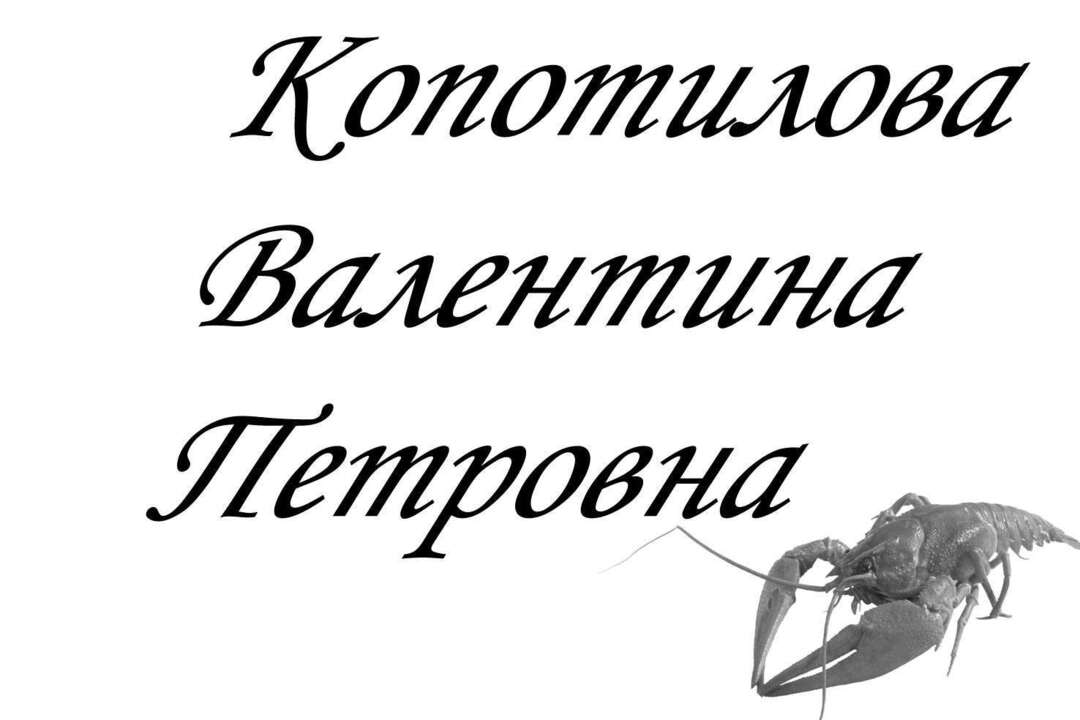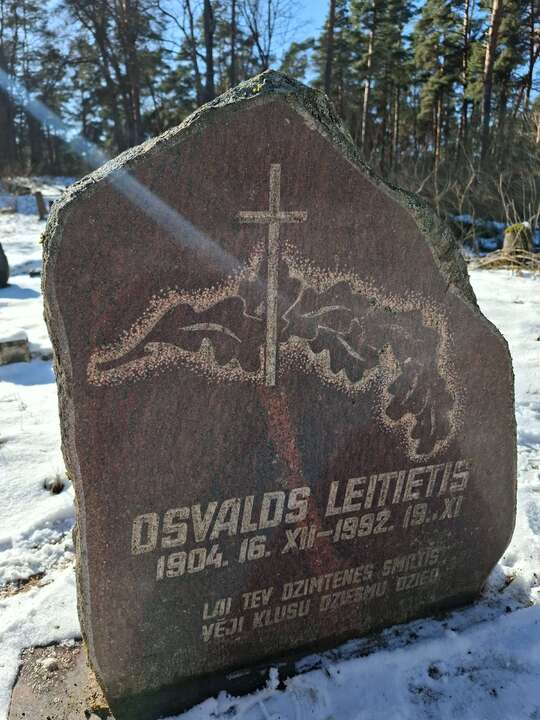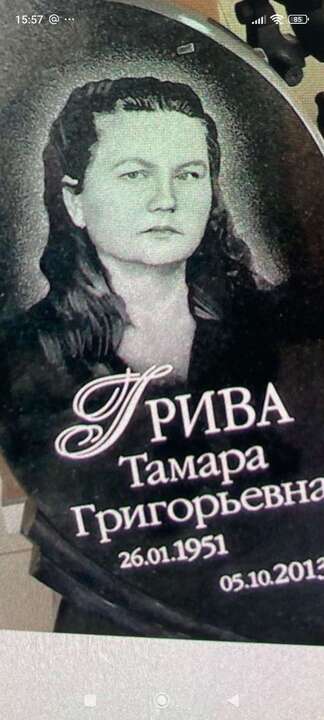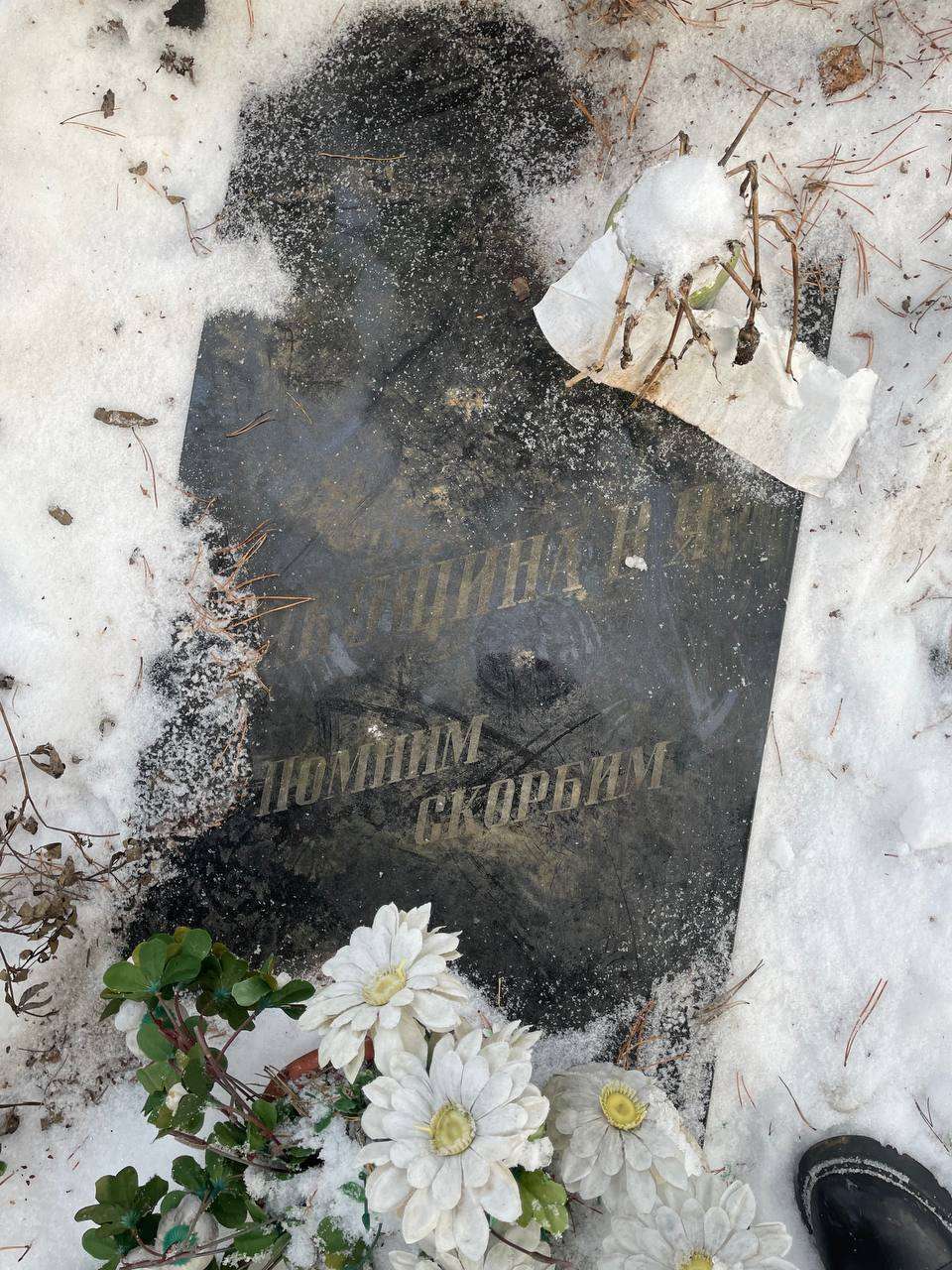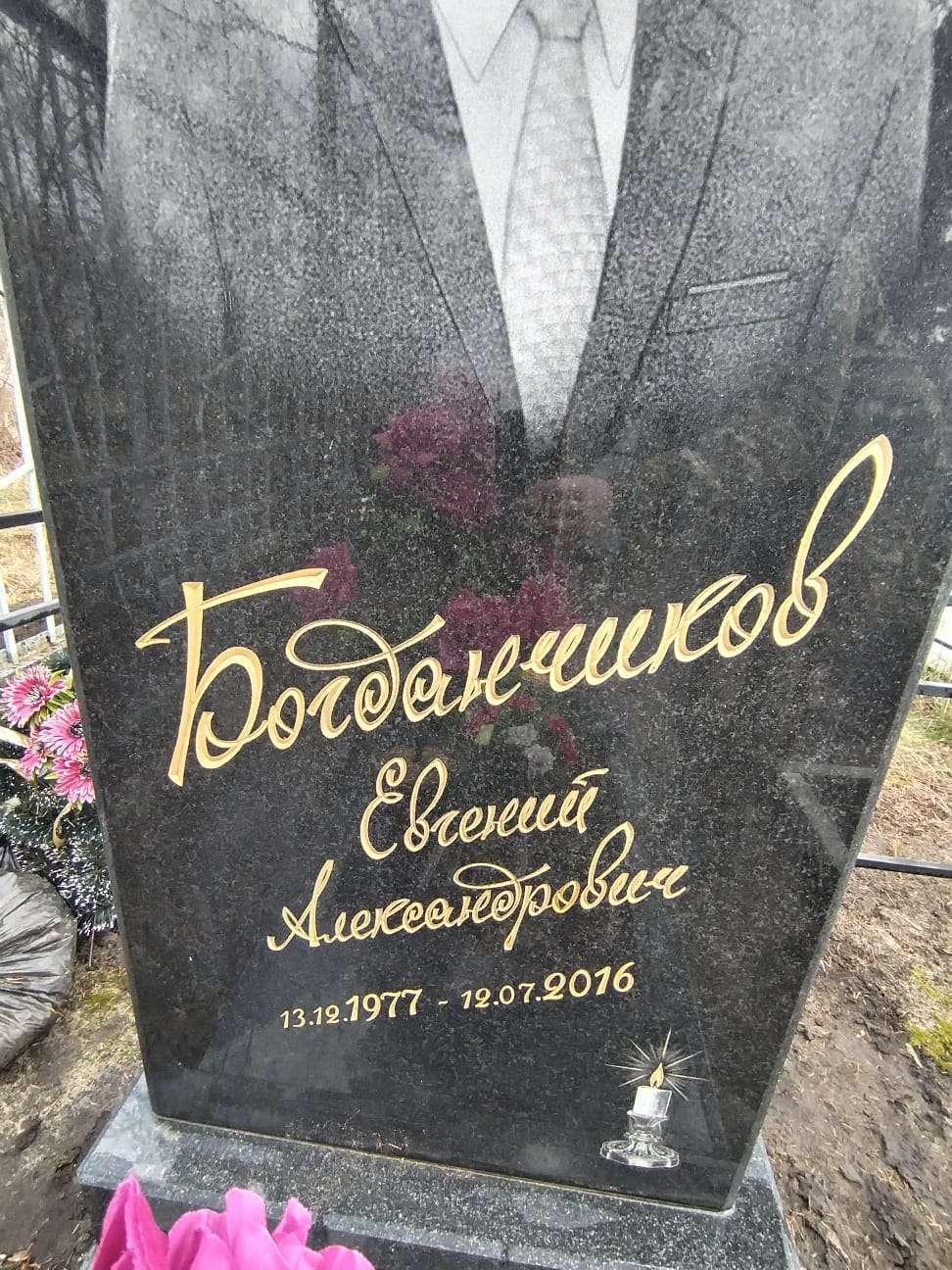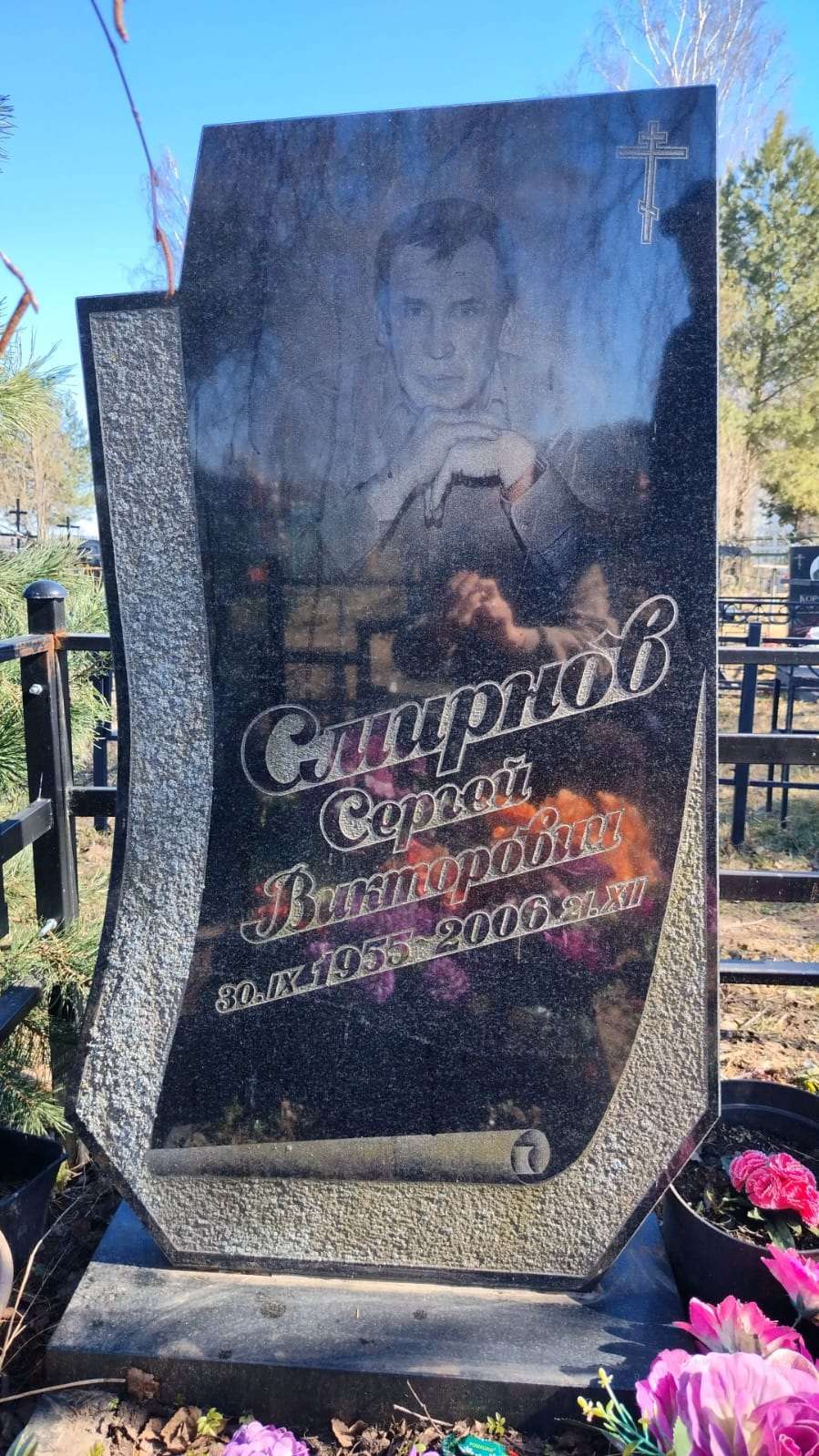
Aidar606 Опубликовано 20 марта, 2025 (изменено) Всем здравствуйте , что за шрифт? Изменено 20 марта, 2025 пользователем Aidar606
КатяЛин Опубликовано 25 марта, 2025 Здравствуйте. Подскажите, буква Г - какой шрифт?
Arturs Опубликовано 27 марта, 2025 Добрый день Помогите пожалуйста найти шрифт или что-то похожее
алена Опубликовано 27 марта, 2025 @Arturs Так гротеск шрифт ( брусковой) их много.
алена Опубликовано 27 марта, 2025 @Arturs Посмотри вот это: Days Regular Airport Regular - этот чуть "А" одправить a_ConceptoNr Bold 1
Storn Опубликовано 27 марта, 2025 @Arturs это простые латышские парни с Болдерая делали вручную 1 2
Arturs Опубликовано 27 марта, 2025 1 минуту назад, Storn сказал: @Arturs это простые латышские парни с Болдерая делали вручную Ага, только осталось сейчас подобрать что-то похожее
AndreyV Опубликовано 5 апреля, 2025 Добрый день! Подскажите пожалуйста, что за шрифт?
УльянаЛ Опубликовано 7 апреля, 2025 Помогите найти шрифт подходящий. Кроме Боярского @УльянаЛ
domestic Опубликовано 9 апреля, 2025 2 часа назад, Aidar606 сказал: Добрый день, подскажите шрифт Ваш скорее всего ручной, но похож, очень, на мой любимый 2